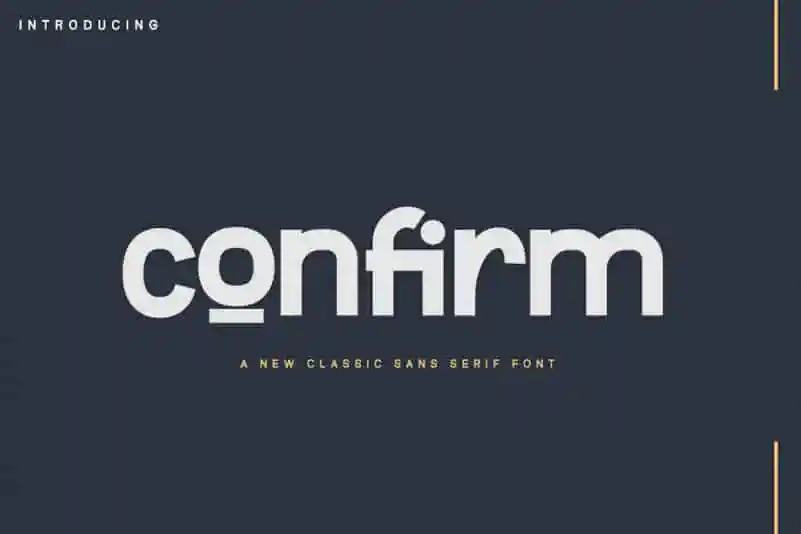
Confirm Sans Serif Font – Download Grátis
A fonte Confirm Sans Serif é uma escolha perfeita para aqueles que buscam uma tipografia inovadora com diferentes características em cada letra. Ela se destaca especialmente nas letras maiúsculas, oferecendo um estilo único e distintivo. Esta font foi criada como resposta a uma necessidade de design novo e inspirador, trazendo variedade e elegância aos textos. Quando você escrever nome ou frases com sua seleção ampla de alternativas de letras, ela cria um impressionante aspecto de luxo e beleza. Ideal para aplicativos digitais, impressões modernas e qualquer projeto que busque unidade estética e atitude fresca em seu design. Certamente é uma fonte que vai tornar sua produção visual mais interessante e única.